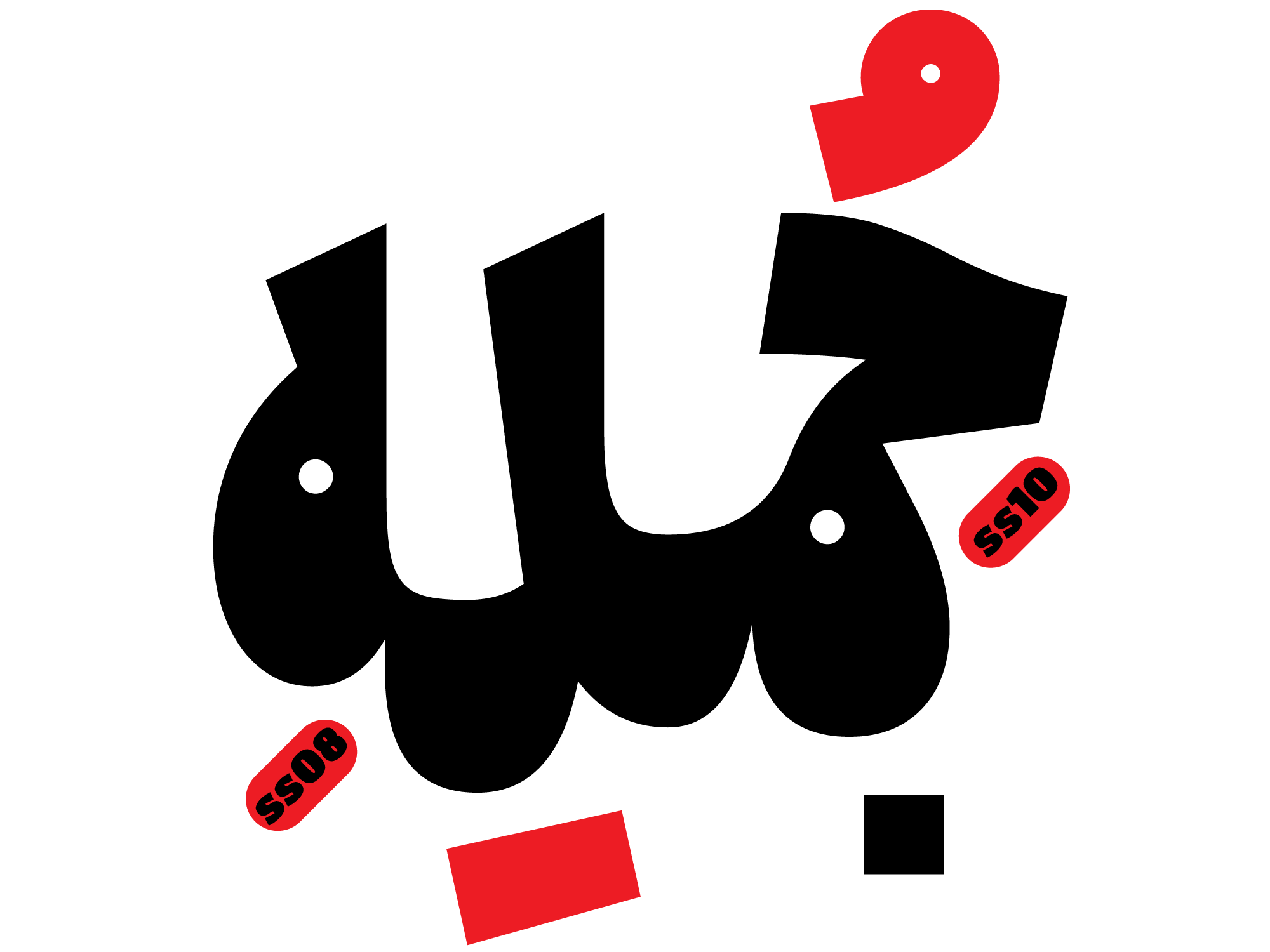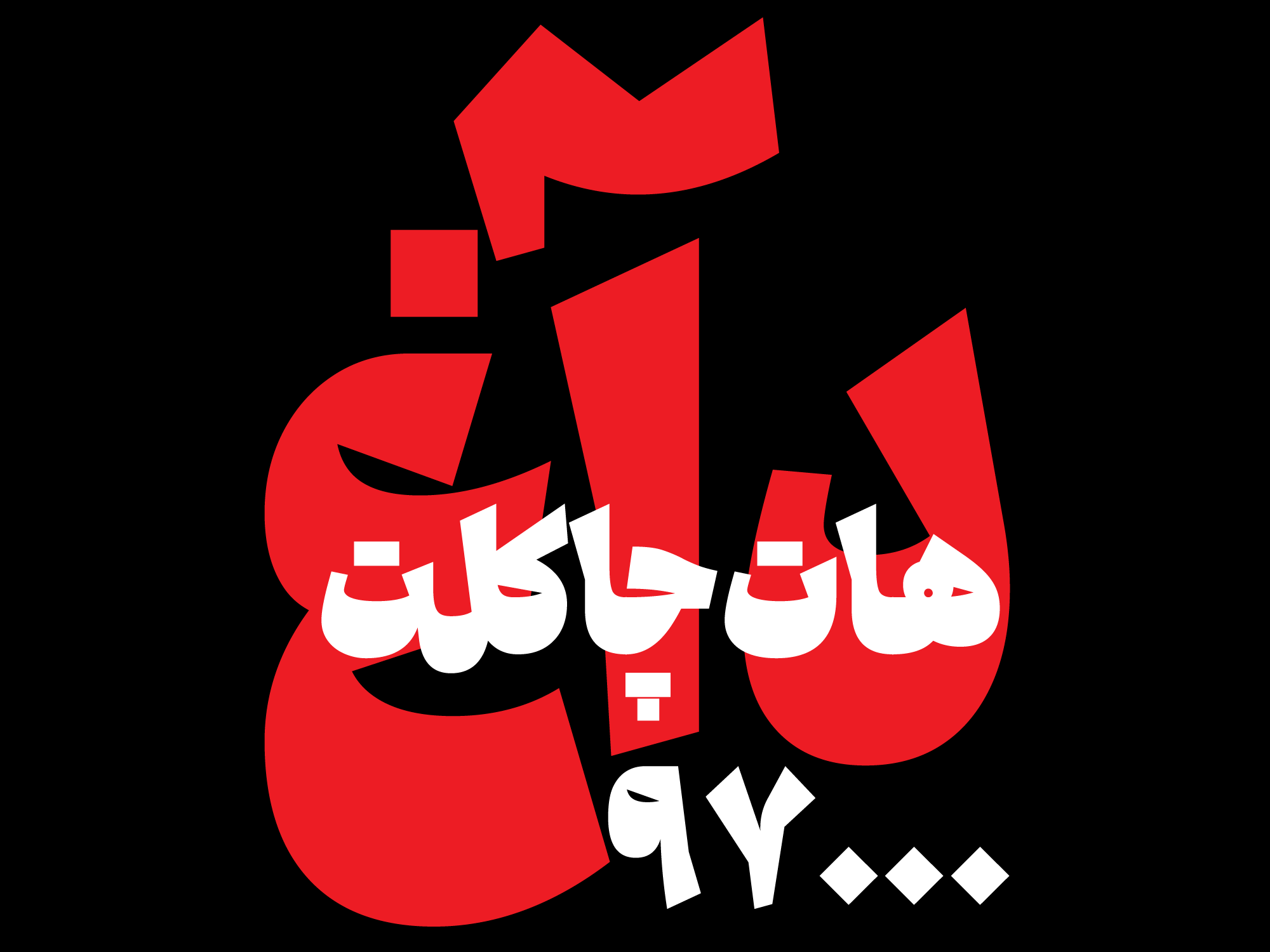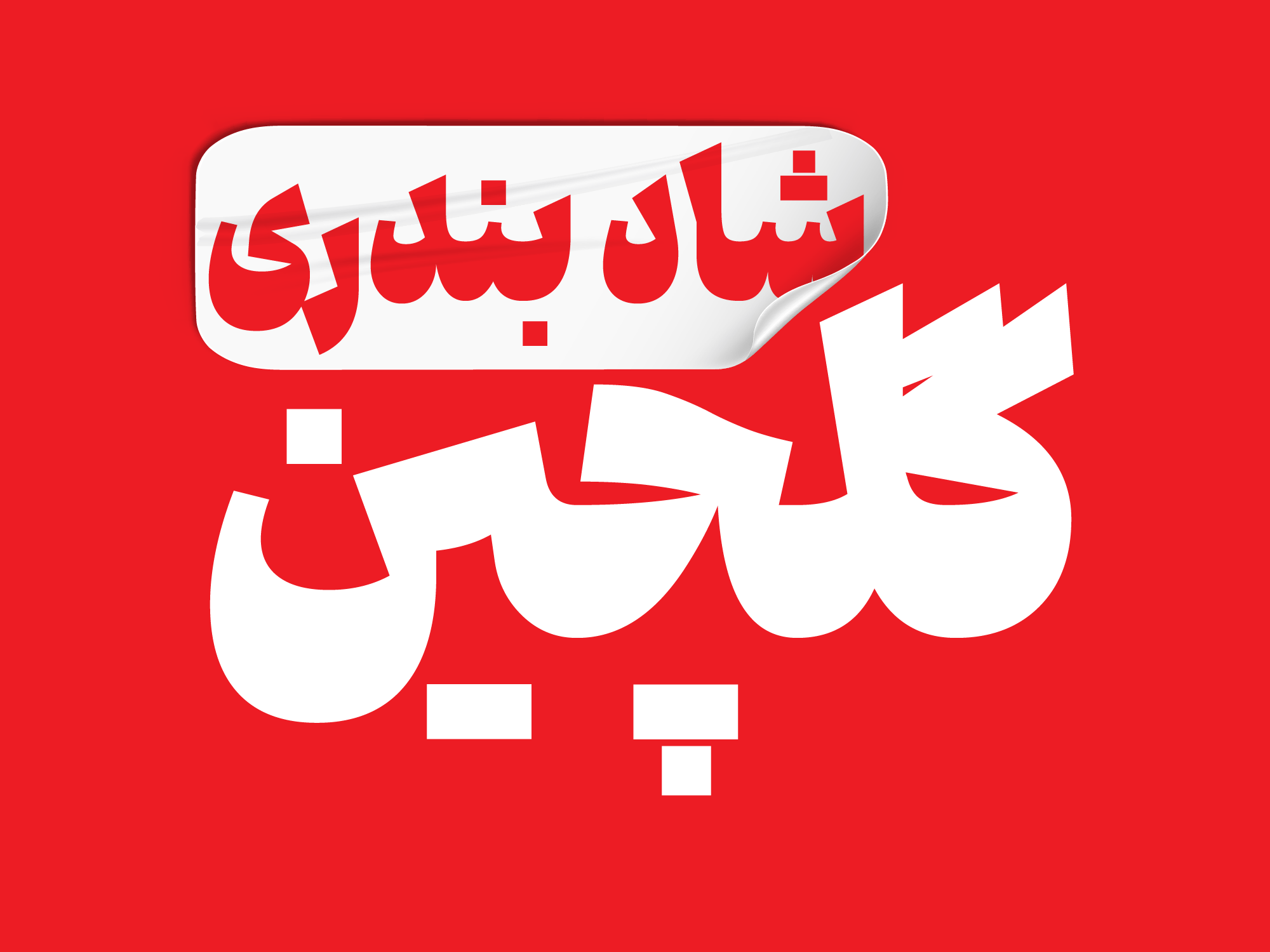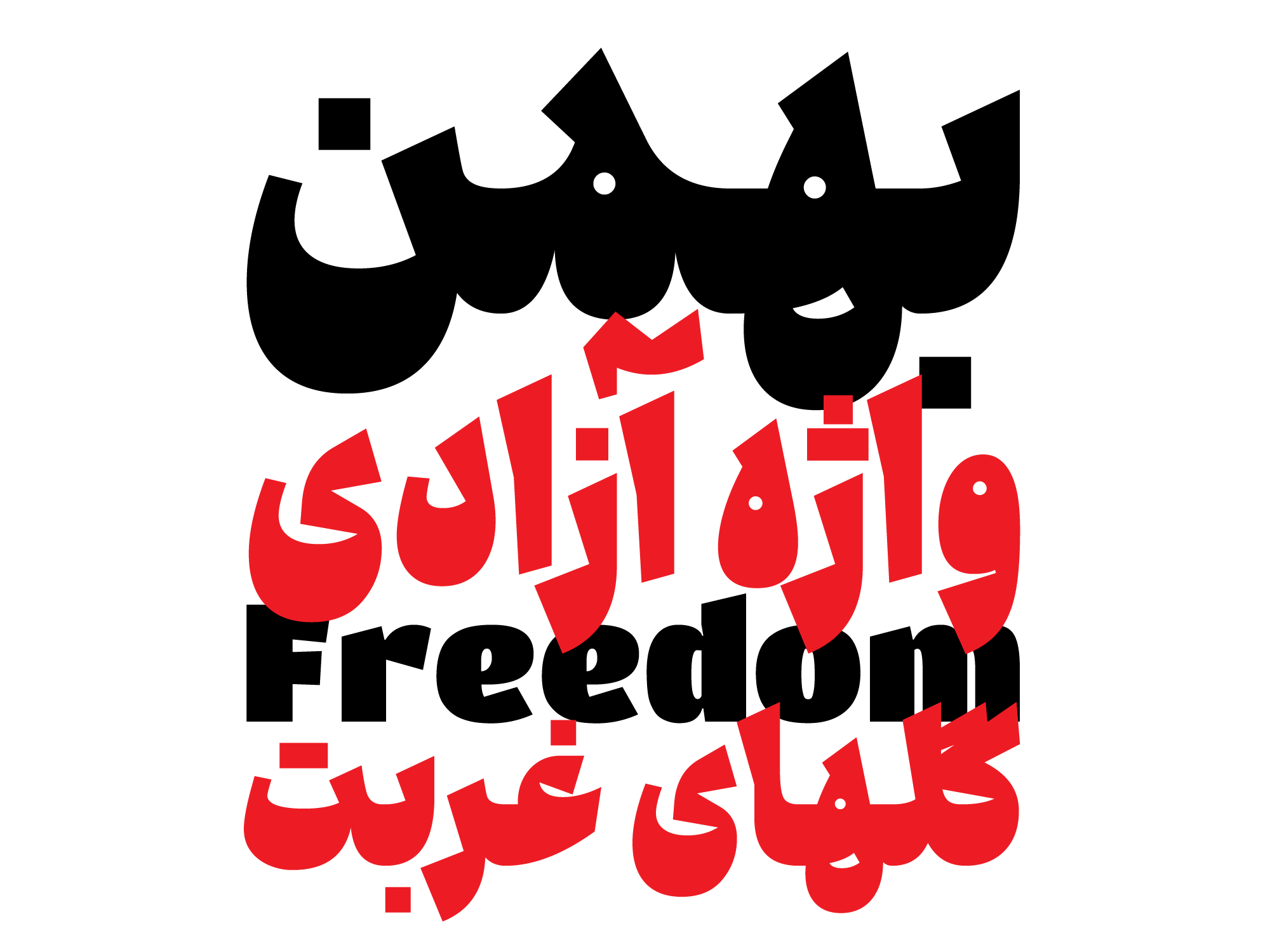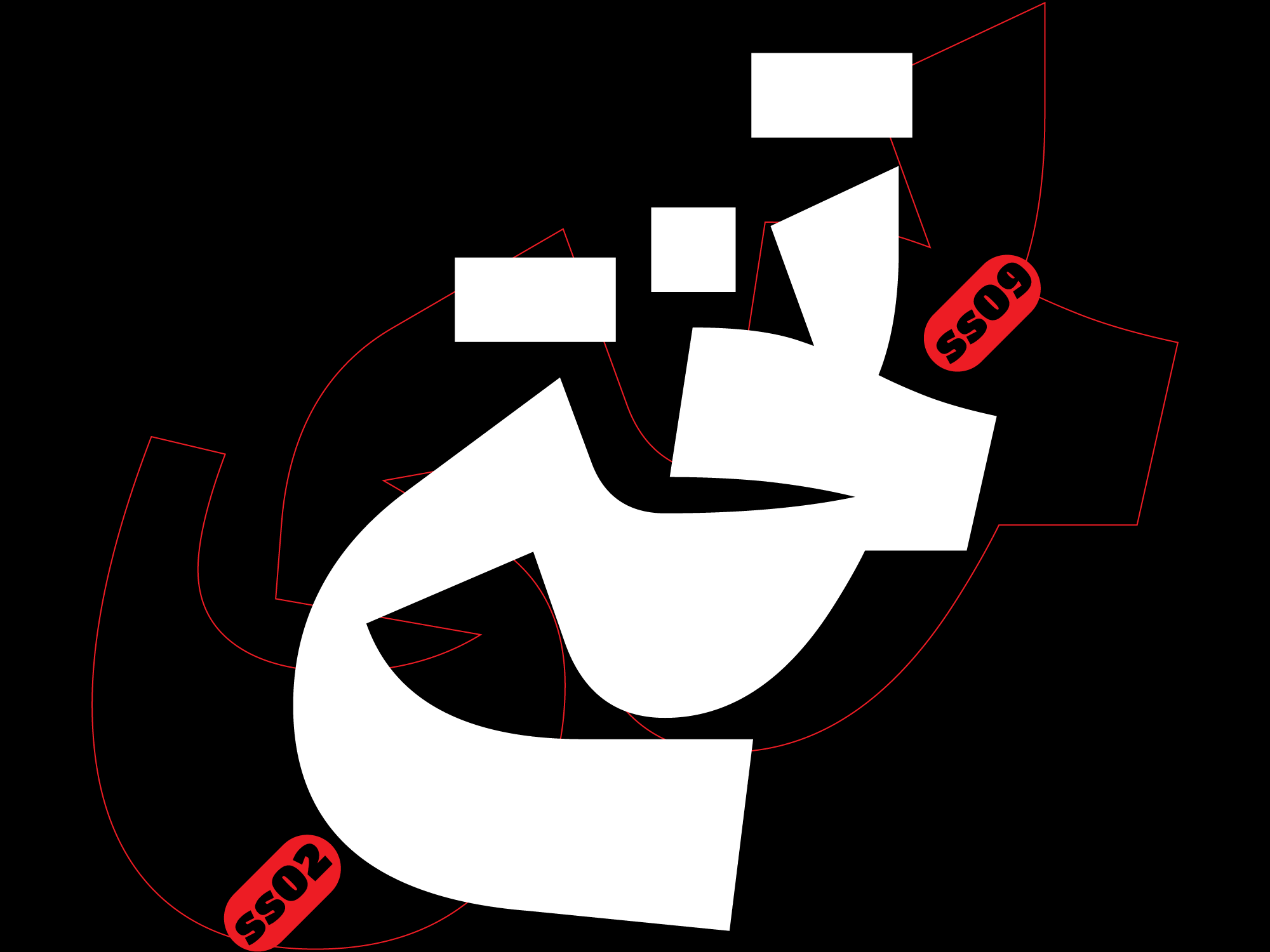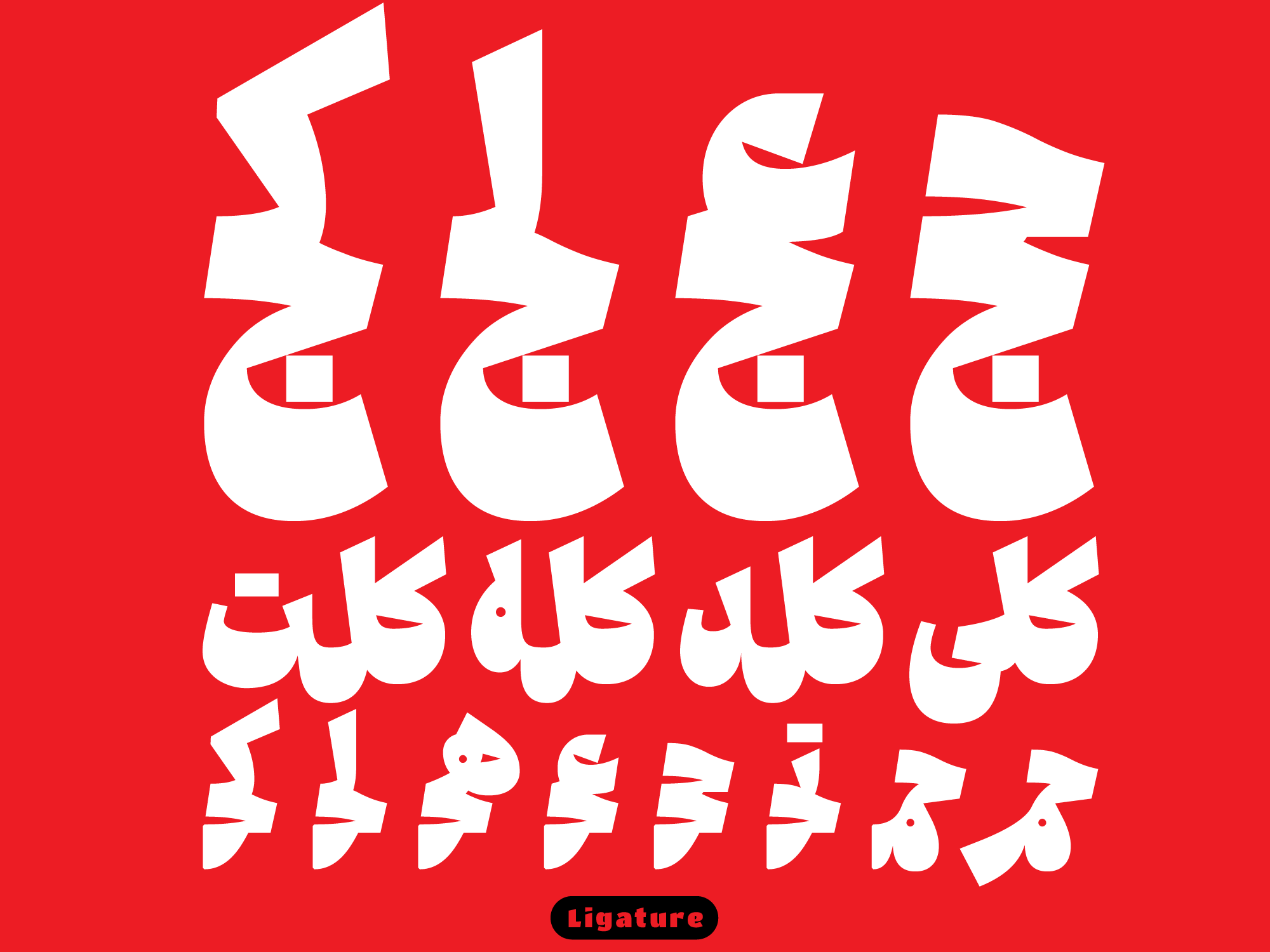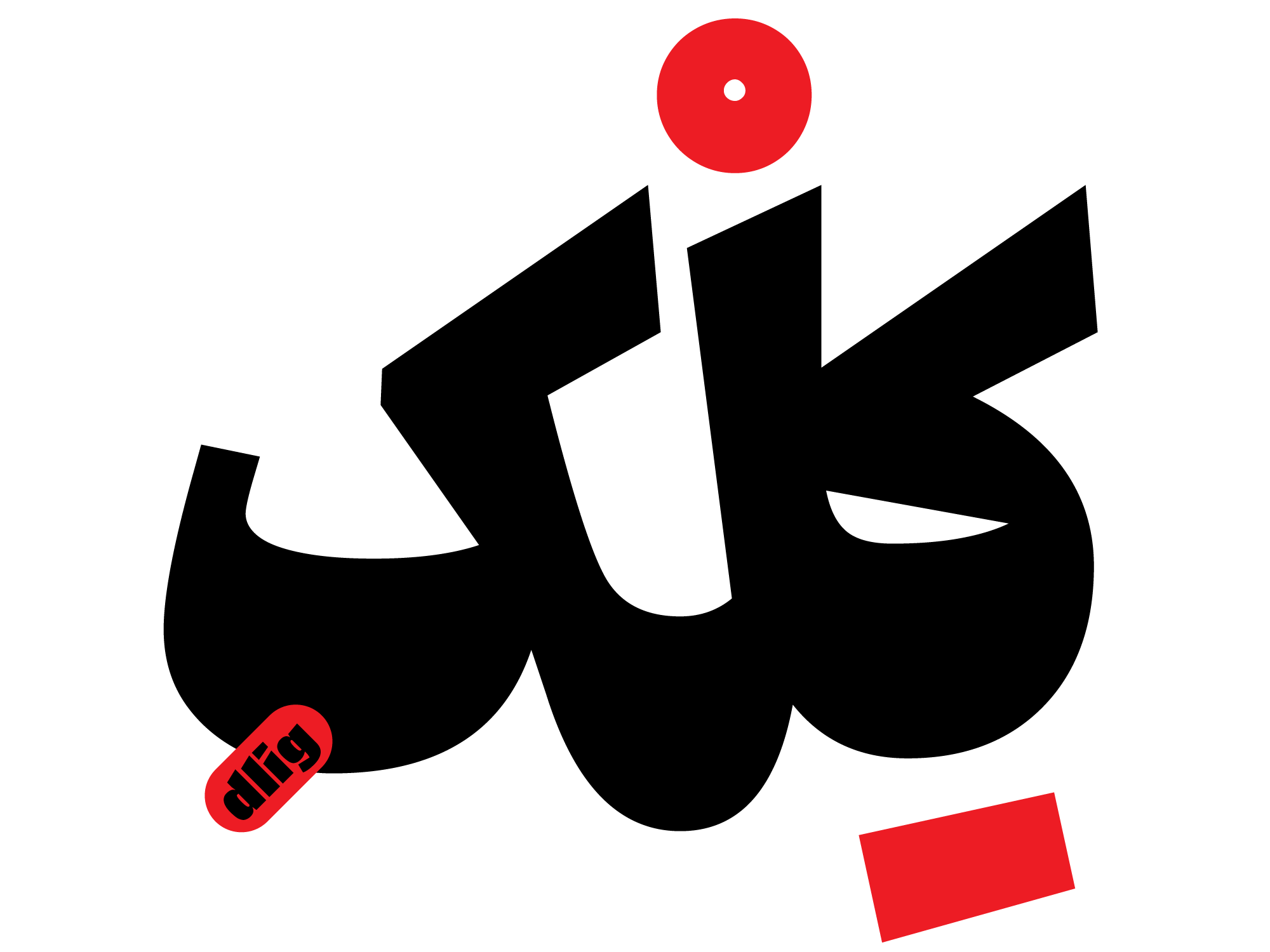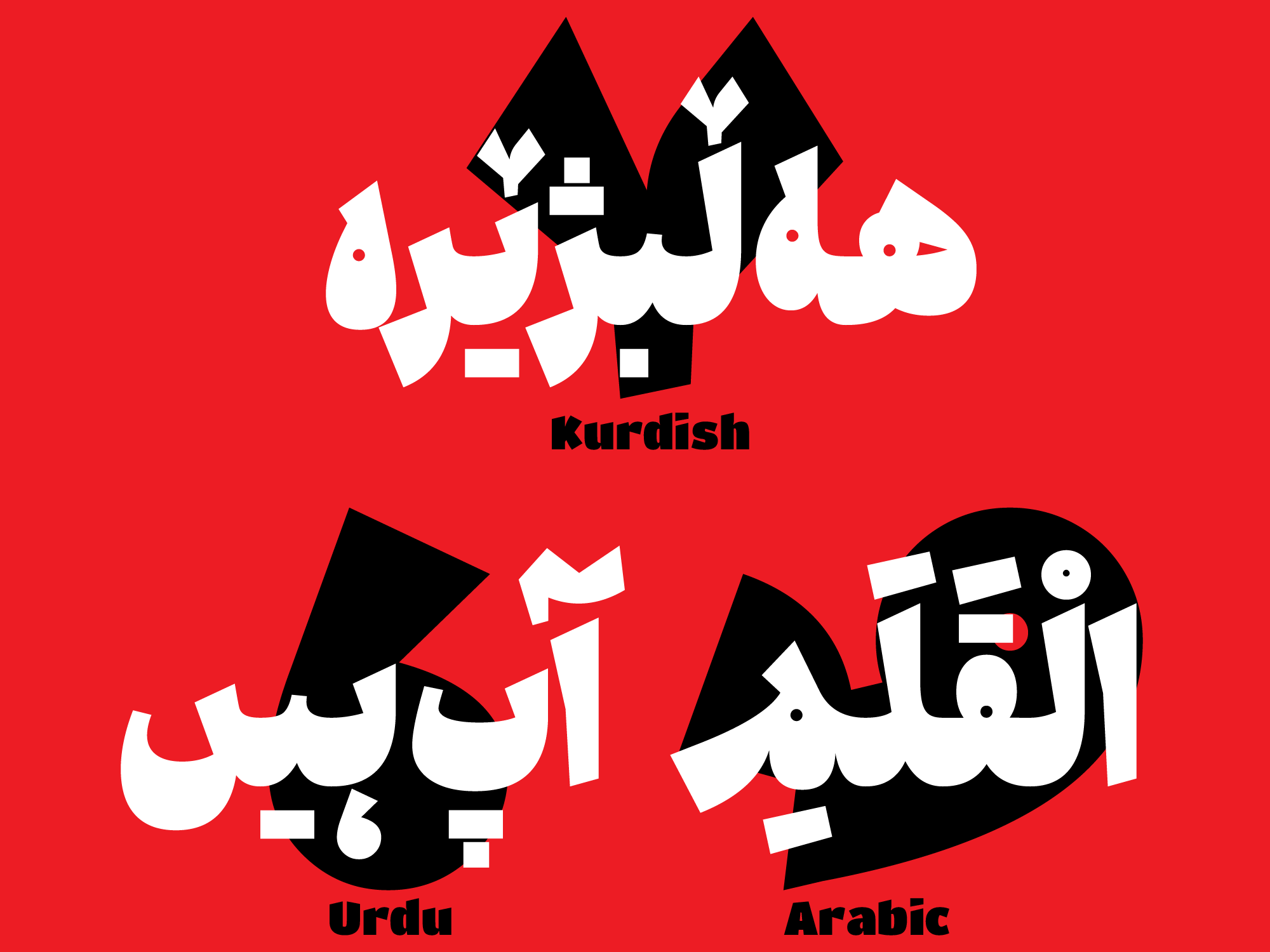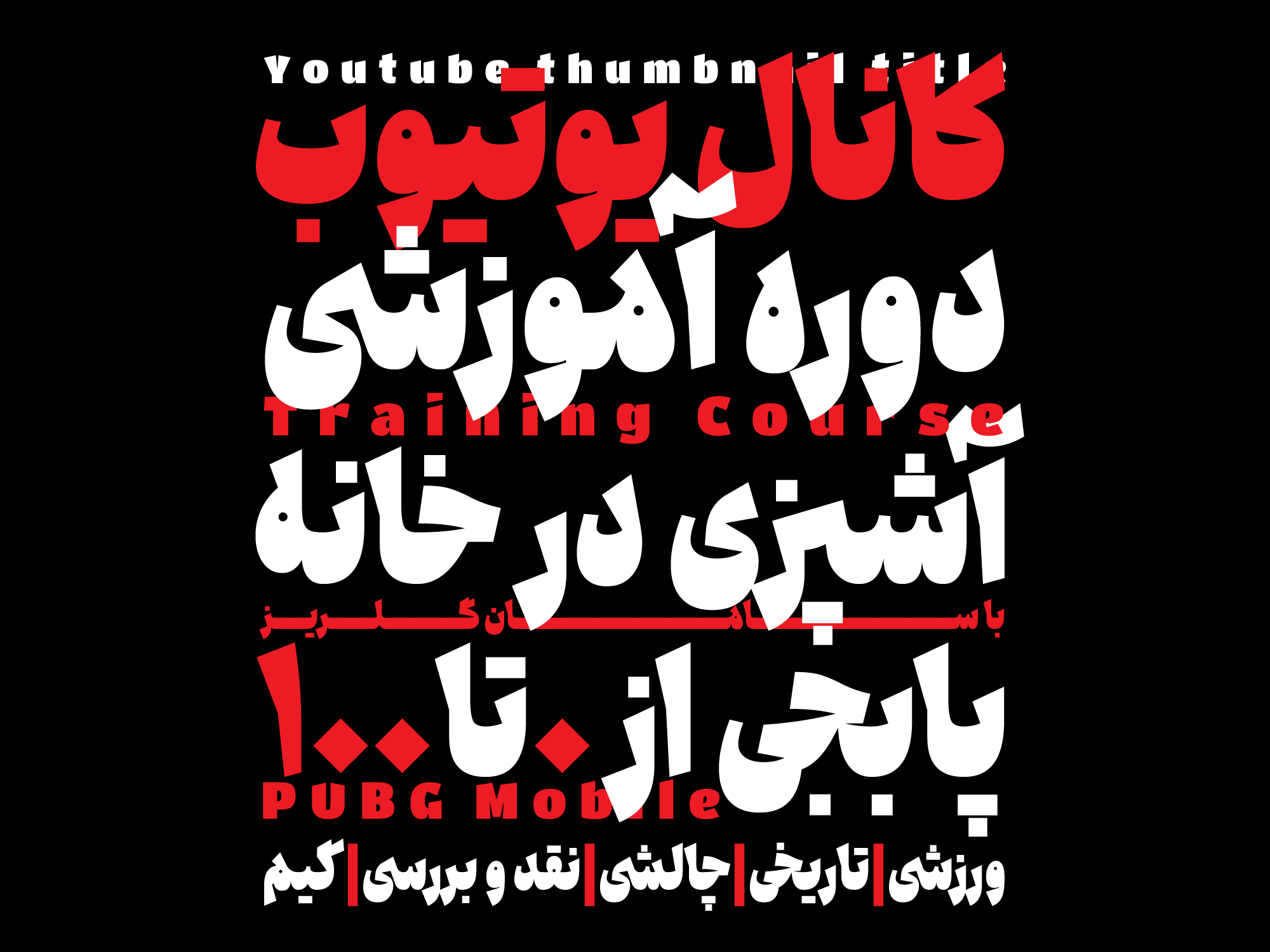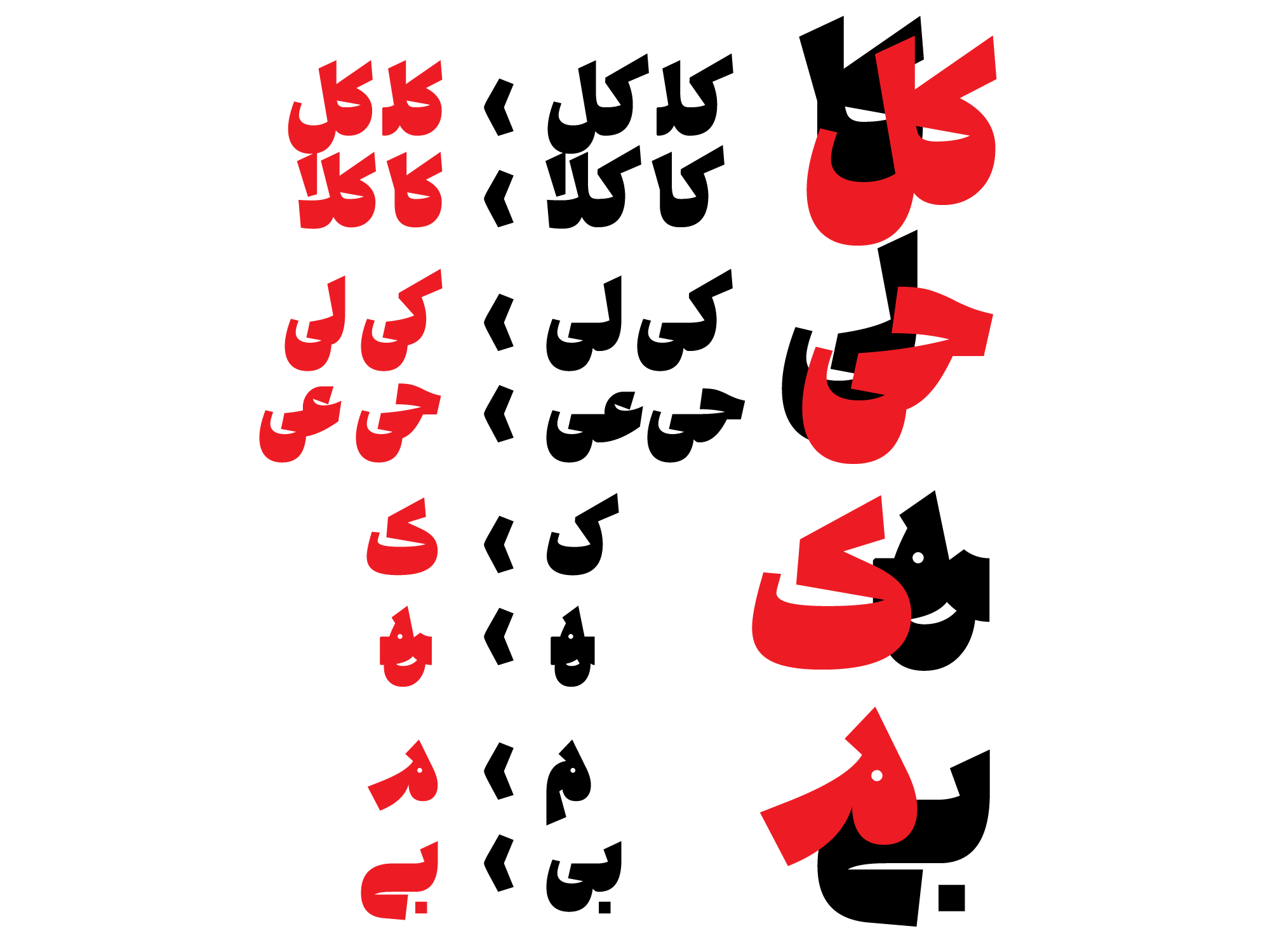
از ایده تا اجرا
ایده این تایپفیس در کلاس طراحی تایپ استاد ناصر خادم (زمستان ۱۴۰۳) مطرح و زیر نظر ایشان کامل شد. اولین حرف «ـه» بود که فرم آن به دو بخش تیز و منحنی تقسیم و همین ایده برای تمام حروف اجرا شد.
در طراحی آن تلاش کردم که حروف تا حد ممکن متفاوت طراحی شوند تا یک فونت تیتر جذاب نیمه فانتزی و در عین حال خوانا داشته باشیم. استفاده در پوستر فیلم و نمایش، تیتر مطالب تبلیغاتی و تولید محتوای فضای مجازی از کاربردهای آن است.
جایگزین ها
حروف و ترکیبات دو و سه حرفی جایگزین متعددی در فونت جمله وجود دارد که با استفاده از راهنمای فونت میتوان از آنها استفاده کرد. در آپدیت آینده نیز ترکیبات بیشتر به آن اضافه خواهد شد.
پشتیبانی از زبان عربی، انگلیسی، اردو و کردی
فونت جمله برای زبان فارسی و عربی طراحی شده است و زبانهای اردو، کردی و انگلیسی را نیز پشتیبانی میکند. برای فونت انگلیسی آن از فونت اوپن سورس TitanOne استفاده شده است.
نقطهها
در فونت جمله نقاط به دو شکل مربع و دایره در دسترس هستند.